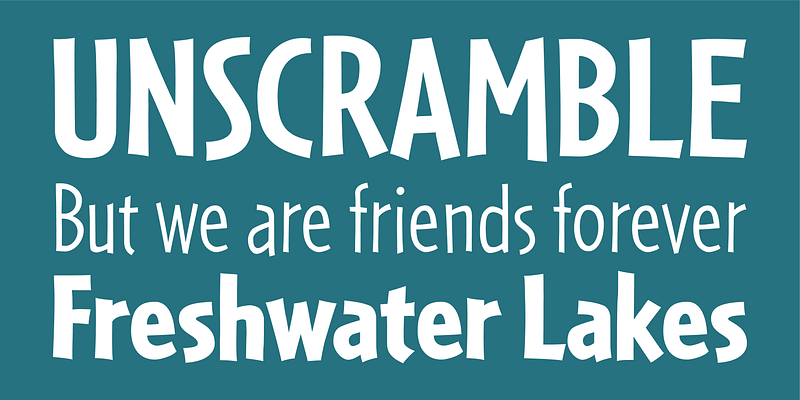
Die normalerweise in einer Handschrift zu findenden Unregelmäßigkeiten können auch serifenlose Buchstabenformen beleben. Bei Cafeteria achtete Tobias Frere-Jones besonders darauf, Aktivität und Lesbarkeit in Einklang zu bringen, und zeichnete eine serifenlose Freiform, die verdichtet, aber keineswegs steif ist.